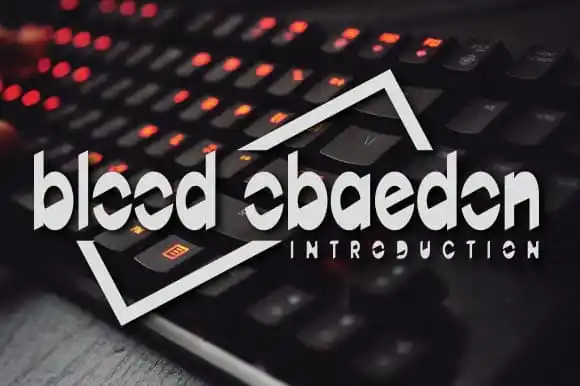
Blood Obaedon Display Font – Download Grátis
A Blood Obaedon Display Font é a mais recente evolução na arquitetura serif das letras digitais, perfeita para ambientes que valorizam uma aposta elegante e sofisticada. Perfeito para estilos de publicidade com personalidade, esta fonte traz um toque único aos logos de redes sociais, posts e identidades visuais de marcas. Ela também é ideal para embalagens de produtos, etiquetas em lojas físicas ou online, ilustrações, e até mesmo como fundo de fotografia. Seu design elegante se destacará em qualquer projeto que busque adicionar um toque de graciosidade às suas criações digitais. Com o designer andikastudio à sua disposição, a Blood Obaedon Display Font é uma escolha perfeita para quem busca criatividade e sofisticação sem comprometer a elegância da tipografia serif.